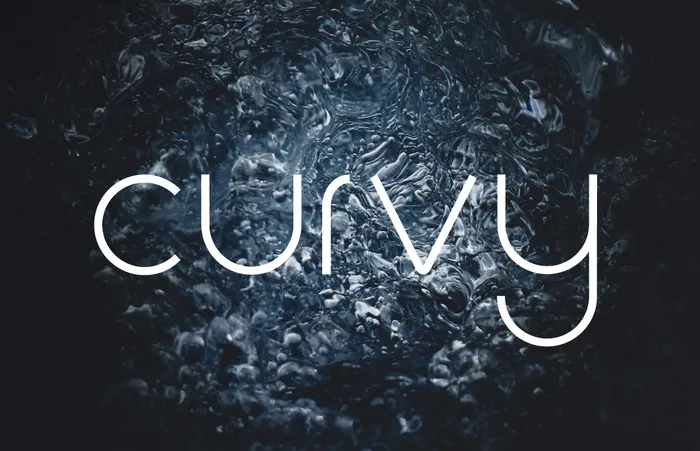
Aqui está uma descrição em português para a página de download da fonte “Curvy Font”, seguindo as instruções: Esta é uma nova e gratuita fonte tipográfica, criada por Riccardo Mecheri. Chama-se Curvy Font e tem um design arredondado inspirado em formas geométricas redondas. Perfeito para sua próxima iniciativa, pode ser utilizada em convites, cartões de notas, camisetas e muito mais, oferecendo um apelo elegante e natural que imita escrita a mão. Curvy é uma font sem serif que traz frescura à tipografia moderna, tornando-a ainda mais versátil para diversas aplicações visuais. Essa fonte é perfeita para quem busca algo único e descomplicado, que atinge um público com seu visual suave e reconfortante. A fonte Curvy foi desenvolvida por Hamilton e está disponível gratuitamente, tornando-a uma excelente opção para designers independentes ou aqueles que buscam fontes profissionais sem pagar altos royalties. É perfeitamente adequada para criações que precisam de um toque único e personalizado, seja para identidade visual, design gráfico ou até mesmo para elementos digitais como ícones e emojis. Curvy é uma excelente adição à sua coleção de fontes se você está buscando algo moderno e versátil sem comprometer o estilo arredondado que tanto gosta.